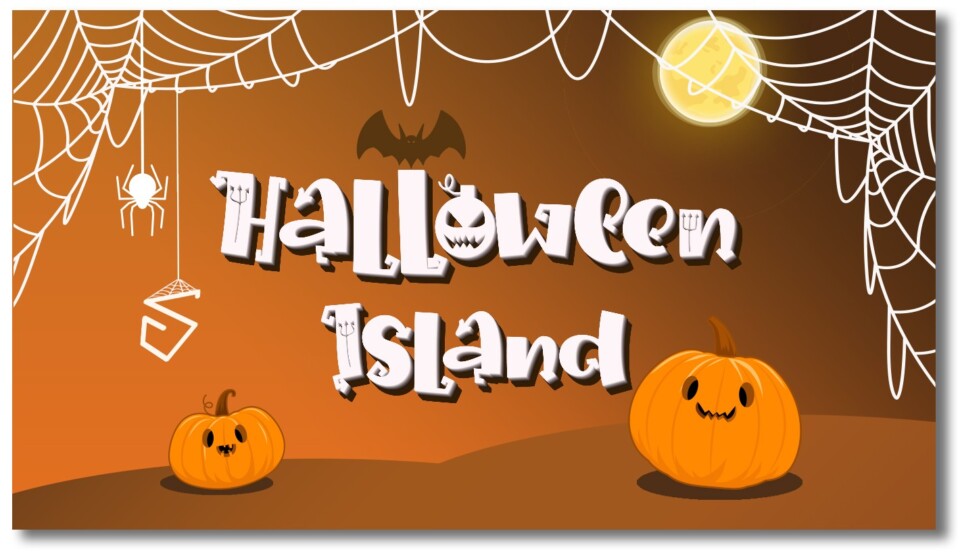
Font việt hóa Sayuri Halloween Island
Giới thiệu về Font việt hóa Sayuri Halloween Island
Chào mừng bạn đến với thế giới sáng tạo đầy màu sắc cùng bộ Font việt hóa Sayuri Halloween Island. Đây là một phông chữ đặc biệt mang phong cách vui nhộn nhưng không kém phần kỳ bí, rất phù hợp cho các dự án thiết kế liên quan đến lễ hội Halloween. Nếu bạn đang tìm kiếm một Font Miễn Phí để làm mới các bài giảng, tờ rơi hay trang trí báo tường tại trường học, thì đây chính là lựa chọn hoàn hảo nhất. Bộ font này không chỉ giữ nguyên nét vẽ tinh nghịch ban đầu mà còn được tối ưu hóa tiếng Việt giúp bạn sử dụng dễ dàng hơn bao giờ hết.
Ưu điểm của Font việt hóa Sayuri Halloween Island trong thiết kế
Nét vẽ thủ công độc đáo
Đặc điểm nổi bật của Font việt hóa Sayuri Halloween Island nằm ở những đường nét uốn lượn tự nhiên, tạo cảm giác như được vẽ tay bởi những nghệ sĩ tài ba. Những ký tự có hình dáng tròn trịa, đôi chút biến tấu ma mị giúp khơi gợi trí tưởng tượng phong phú cho học sinh và giáo viên. Phông chữ này giúp các biểu ngữ trở nên sinh động và thu hút ánh nhìn ngay lập tức.
Khả năng ứng dụng đa dạng
Không chỉ giới hạn trong các tấm thiệp mời tiệc hóa trang, phông chữ này còn cực kỳ hiệu quả khi dùng để thiết kế tiêu đề sách, nhãn dán dụng cụ học tập hoặc các video thuyết trình sinh động. Sự tương thích cao với nhiều phần mềm đồ họa hiện nay giúp quá trình thiết kế trở nên nhanh chóng và chuyên nghiệp.
Kết luận về bộ phông chữ đặc sắc